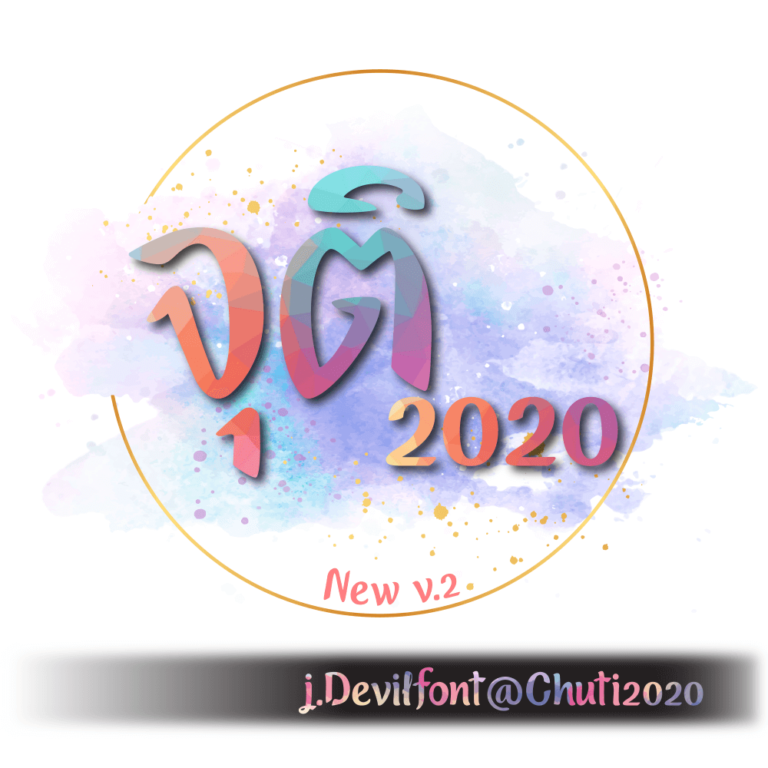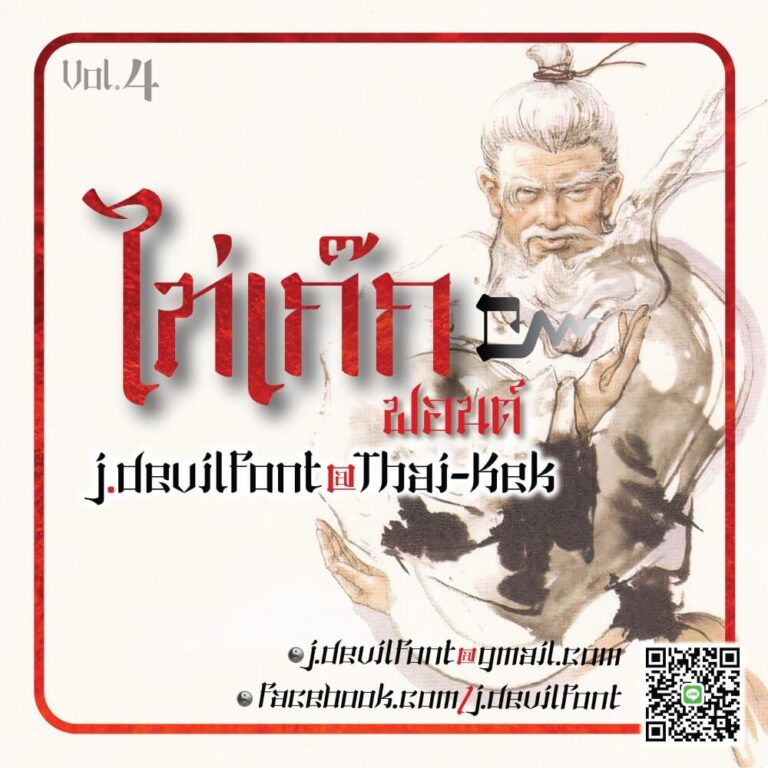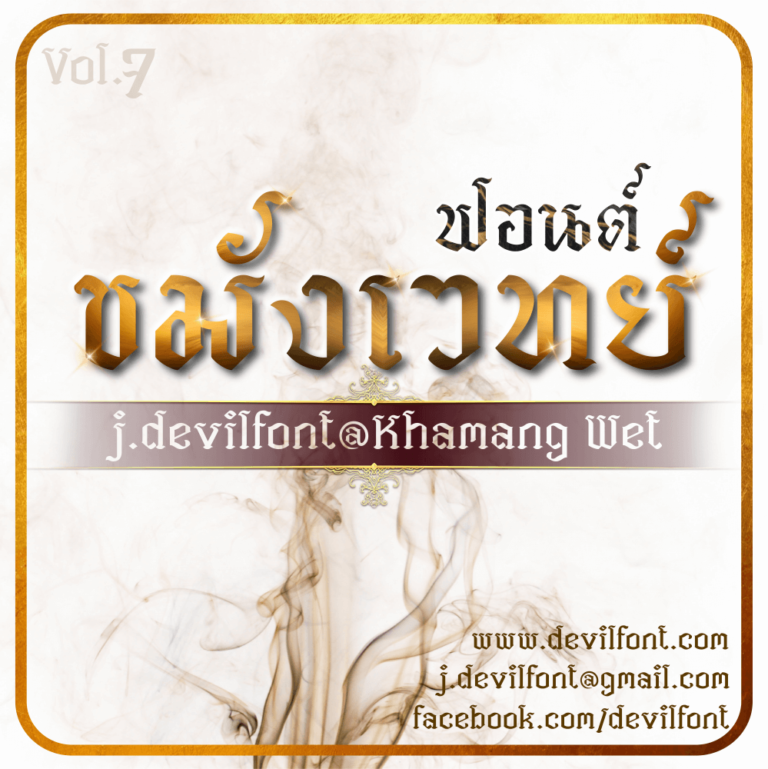
j.devilfont
สร้างสรรค์ฟอนต์ไว้ทั้งหมด 17 ตัว
รวมสมัย (j.devilfont@ruam samai plus)
ผลงานฟอนต์ชุดที่ 18 รวมสมัย – ลักษณะฟอนต์ไทย พาดหัว งานป้าย งานไม้ งาน CNC บทกลอน ป้ายร้านค้า ร้านทอง สายมู ไพ่ยิปซี ไพ่ทาโร่ ปกนวนิยาย นิตยสาร เทศกาล ศาลเจ้า ของโบราณ โลโก้ สกรีนเสื้อ แสดงงานพิธี สารคดี สื่อโฆษณา แบรนด์สินค้า ความเป็นเอกลักษณ์ไทยโบราณร่วมสมัย
สถิต (j.devilfont@Sathit)
ฟอนต์ สถิต ผลงานฟอนต์ชุดที่ 17 – ลักษณะฟอนต์ไทย พาดหัว งานป้าย งานไม้ งาน cnc บทกลอน ป้ายร้านค้า สายมู ปกนวนิยาย นิตยสาร เทศกาล ศาลเจ้า ของโบราณ โลโก้ สกรีนเสื้อ แสดงงานพิธี สารคดี สื่อโฆษณา แบรนด์สินค้า ความเป็นเอกลักษณ์ไทยโบราณร่วมสมัย
ปฐพีสายฟ้า (j.devilfont@Pathapee-Saifah)
ฟอนต์ ปฐพีสายฟ้า ผลงานฟอนต์ชุดที่ 16 – ลักษณะฟอนต์ไทย พาดหัว งานป้าย งานไม้ งาน cnc บทกลอน ป้ายร้านค้า สายมู ปกนวนิยาย นิตยสาร เทศกาล ศาลเจ้า ของโบราณ โลโก้ สกรีนเสื้อ แสดงงานพิธี สารคดี สื่อโฆษณา แบรนด์สินค้า ความเป็นเอกลักษณ์ไทยโบราณร่วมสมัย
เธอ (j.devilfont@Tur)
ผลงานฟอนต์ที่ตัว 11 ชื่อฟอนต์ เธอ ลักษณะฟอนต์ไทย เล่นหาง พาดหัว หรือ เนื้อหาบทความได้ งานป้าย บทกลอนร้านทอง สายมู ปกนวนิยาย พระเครื่อง โบราณ แสดงความเป็นเอกลักษณ์ไทยร่วมสมัย อ.จินดา เนื่องจำนงค์ ฯลฯ
คเณศน้อย (j.devilfont@Kanet Noi)
นำเสนอผลงานตัวที่ 10 ฟอนต์ คเณศน้อย ลักษณะฟอนต์ไทย เล่นหาง พาดหัว อักษรวิจิตร หรือ เนื้อหาบทความได้ งานป้าย ร้านทอง สายมู ปกหนังสือ นวนิยาย ร่วมสมัย งานอักษร 3D ฯลฯ
ขมังเวทย์ ปลายมน (j.devilfont@Khamang Wet)
ผลงานฟอนต์ที่ตัว 9 ชื่อฟอนต์ ขมังเวทย์ ปลายมน เป็นชุดอักษรไทยโบราณ ที่ต่อยอดจาก ขมังเวทย์ ปลายแหลม V1 เพิ่มอักษร เพิ่มลูกเล่น
สุดสาคร (j.devilfont@Sudsakorn)
ผลงานฟอนต์ที่ชุด 8 ชื่อฟอนต์ สุดสาคร  ลักษณะฟอนต์ไทย เล่นหาง พาดหัว หรือ เนื้อหาบทความได้ นิยาย โบราณ
ตะมุตะมิ (j.devilfont@TamuTami)
ผลงานฟอนต์ที่ตัว 6ตะมุตะมิ มีความหมายว่า น่ารักน่าเอ็นดูนั่นเองตัวฟอนต์ต้องการแสดงความน่ารัก น่าเอ็นดูออกมาให้เห็นหลายๆ มุมของการออกแบบตัวอักษรไทยครับ มุมิ” A journey of a thousand miles must be with a single step.”
ดริฟท์คิง (j.devilfont@Drift King)
ฟอนต์ตัวที่ 5 ดริฟท์คิง Drift-king ลักษณะฟอนต์พาดหัว ตัวอักษรต้องการความเป็น สปอร์ตตี้ โฉบเฉี่ยวมีความเท่ สไตล์วัยรุ่นเปลี่ยนขาได้ถึง 3 แบบ แล้วแต่ความชอบของผู้นำไปใช้งาน
ไท่เก๊ก (j.devilfont@Thai Kek)
ผลงานฟอนต์ชุดที่ 4 เป็นชุดอักษรไทย สไตล์จีนในชื่อ ไท่เก๊กลูกเล่นยังเป็นเช่นเดิมตามคอนเซปต์ Devilfont
ร่วมสมัย (j.devilfont@ruam samai)
ผลงานชิ้นที่ 3 ฟอนต์ร่วมสมัย ลักษณะตัวอักษรต้องการความร่วมสมัย เรียบหรู บ่งบอกถึงความเป็นไทย รูปแบบฟอนต์สามารถเปลี่ยนขาได้ถึง 4 แบบ แล้วแต่ความชอบของผู้นำไปใช้งานครับ
อาคม2020 (j.devilfont@akhom2020)
หลังจากที่เพื่อนๆ สมาชิกในกลุ่ม ฟอนต์กูรู  #กลุ่มsk #งานสกรีน #งานป้าย เพื่อนๆ ฟรีแลนซ์ที่ช่วยเป็นกำลังใจกับผลงาน ฟอนต์จุติ2020 v.2 ผมกันไปบ้างแล้ว ปัจจุบันผมได้เปิดตัวฟอนต์ตัวที่ 2 ชื่อ อาคม2020 แนวอาลักษณ์กันบ้าง